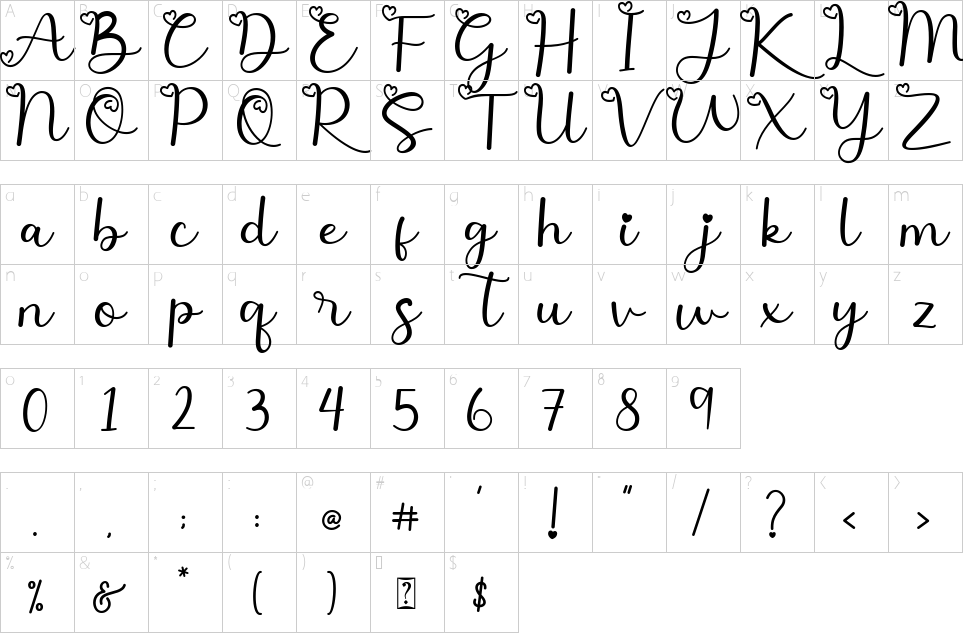
Descubra a delícia que é usar a fonte Almost Valentine para sua próxima obra de arte. Esta elegante fonte foi criada por AEN Creative Studio, e já foi baixada mais de 4.311 vezes. Perfeita para celebrar o amor ou apenas para uma mensagem especial, Almost Valentine traz uma sensação de nostalgia que vai encantar seus leitores. Descubra por que esta fonte é tão popular e imprima seu próprio toque de amor com essa fonte. Não perca mais tempo, baixe Almost Valentine agora e dê um toque especial ao seu design.